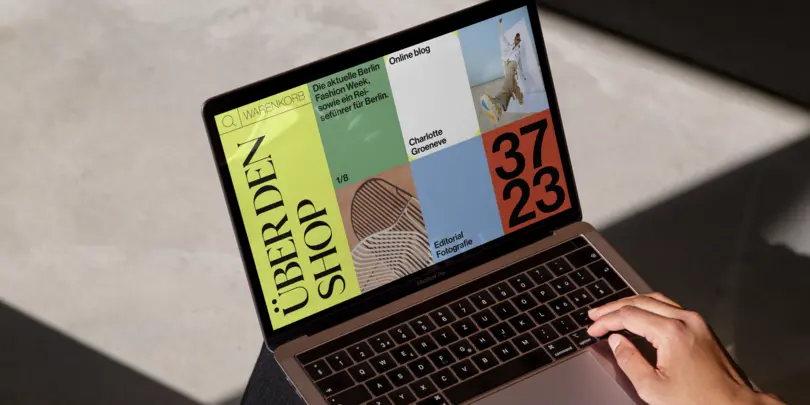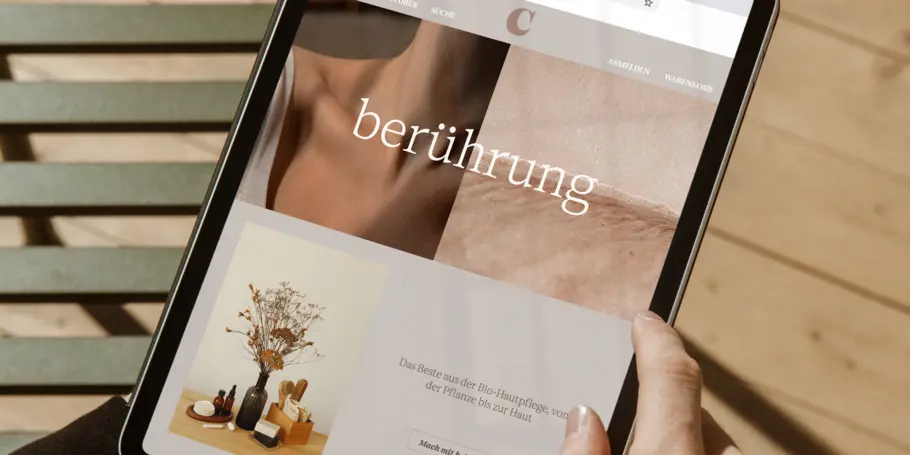
Wie ein verstärkter Fokus auf die digitale Transformation die Markenerwartungen der Kunden verändert hat.
„ Unabhängig von der Mission Ihrer Marke ist die Schrift entscheidend für den Aufbau und die Pflege Ihrer Kundenbeziehung. “
In den letzten zehn Jahren hat sich der digitale Wandel dramatisch auf die Kreation ausgewirkt. Wir haben erlebt, wie sich Marken vom Verkaufen zum Geschichtenerzählen bewegt haben. Und es sind die Kreativen, die diese Geschichten schreiben.
Vor nicht allzu langer Zeit fand das Marketing ausschließlich in Printmedien statt. Heute findet fast alles digital statt. 89 Prozent aller Unternehmen haben bereits eine „digital first“-Strategie eingeführt oder planen, dies zu tun. Und 91 Prozent der Unternehmen sind in irgendeiner Form an digitalen Initiativen beteiligt.
Wenn wir die Entwicklung des Marketings betrachten, war der entscheidende Treiber sicherlich die Verbreitung der mobilen Technologie. Doch die Corona-Pandemie war der Moment, an dem sich alles änderte. Das Abstandhalten und die Regelungen für den Aufenthalt zu Hause förderten die Nachfrage nach digitalen Schaufenstern und mobilen Websites. Dies öffnete die Tür für Innovation und Kreativität, führte aber auch zu einigen Hindernissen auf dem Weg zum neuen Normal.
In einer Welt nach der Pandemie sind die Erwartungen an das Branding so hoch wie nie zuvor.
Die Marke digital vermenschlichen
Während der Pandemie wurden den Kunden das Design, die Werte und die Moral von Marken bewusster als zuvor. Infolgedessen sehen sich Unternehmen mit der neuen Herausforderung konfrontiert, ihren Zweck digital darzustellen. Glücklicherweise können Designer dabei helfen. Neben der Möglichkeit, mit den neuesten digitalen Trends zu experimentieren, hat sich die Schrift zu einem wichtigen Faktor bei der Markenpositionierung entwickelt. Eine Schrift zu finden, die zu Ihren Markenwerten passt, hilft den Kunden, sich mit Ihrer Marke zu identifizieren und eine Verbindung mit ihr einzugehen.
Eine Offenes-Ohr-Mentalität entwickeln
Die Kunden erwarten heute mehr Kommunikation. Untersuchungen zufolge ist Hilfsbereitschaft eine der wichtigsten Erwartungen an Marken. Kunden setzen voraus, dass Marken auf sie eingehen und ein Forum für digitales Feedback bieten. Ob Helpdesk oder Hotline, die Kunden wollen einen Ansprechpartner und einen bilateralen Dialog mit den Marken, denen sie vertrauen. Um diesen Anforderungen zu genügen, müssen Marken jederzeit erreichbar sein und die Erwartungen ihrer Kunden erfüllen. Achten Sie bei der Auswahl der Designelemente für Ihr Branding darauf, dass Sie Schriften wählen, die technisch funktional und gut lesbar sein, damit Sie verlässlich mit Ihren Kunden kommunizieren können. Der Vorteil einer digitalen Präsenz besteht darin, dass Aktualisierungen schneller bei den Verbrauchern ankommen als im Rahmen der analogen Kommunikation.
Lokale und globale Reichweite
Mit der zunehmenden Digitalisierung von Marken ist die Zielgruppe für das Marketing heute internationaler denn je. Das bedeutet, dass digitale Vermarkter auf mehrere Kulturen und Sprachen eingehen müssen, damit sie ihren Markt erreichen. Um auf einer solch globalen Ebene zu kommunizieren, ist es wichtig, dass Sie Ihre Botschaft auf die erweiterten Märkte zuschneiden. Sie sollten Ihr Markenethos und Ihre Werte universell kommunizieren, indem Sie Fonts verwenden, die international funktionieren. Wenn Sie Ihr Leitbild auf Ihrer Website veröffentlichen, sollte das Design der Website darauf abgestimmt sein. Daher ist es wichtig, dass Ihre Fonts viele Sprachen und Schreibsysteme unterstützen und auf globaler Ebene Anklang finden. Ob Sie es glauben oder nicht: 95 Prozent des Webdesigns besteht aus Typografie. Und Studien zeigen, dass Marken weniger als 50 Millisekunden Zeit haben, um einen guten ersten Eindruck zu hinterlassen.
Kontinuierliche Verbesserungen
Eine weitere Herausforderung besteht darin, die sich ständig ändernden Erwartungen der Verbraucher zu erfüllen. In der digitalen Welt ändern sich die Dinge permanent, da stetig neue Technologien entwickelt werden und weil von Marken erwartet wird, dass sie mit den neuesten Trends Schritt halten. Um sich anzupassen, müssen Unternehmen möglicherweise einen Social-Media-Berater einstellen oder neue Technologien erlernen, um mit den Wettbewerbern auf dem Markt mitzuhalten. So haben viele Marken inzwischen eine mobile Website, die ihre Desktop-Site ergänzt. Da 85 Prozent der Erwachsenen der Meinung sind, dass die mobile Website eines Unternehmens genauso gut oder besser sein sollte als die Desktop-Website, haben viele Anbieter sogar eine mobile App eingeführt. Wenn neue Updates des Betriebssystems veröffentlicht werden, muss die App getestet werden, um ihre Funktionalität zu gewährleisten. Wenn Sie mit diesen kontinuierlichen Verbesserungen Schritt halten, wird Ihr Unternehmen auf dem Markt wettbewerbsfähig bleiben.
Loyalität aufbauen
In der digitalen Welt spielt die Schaffung von Vertrauen beim Aufbau eines Kundenstamms eine große Rolle. Laut der aktuellen „Edelman Trust Barometer“-Umfrage kaufen oder befürworten 58 Prozent der Menschen Marken auf der Grundlage ihrer Überzeugungen und Werte. Marken müssen bei ihrer Zielgruppe ein Gefühl der Zugehörigkeit und des Vertrauens aufbauen, um langfristige Kundenerfahrungen zu schaffen. Die Qualität der Designelemente trägt dazu bei, eine einheitliche Stimme zu schaffen, die diese Gefühle unterstützt.
Die Wahl einer Schrift, die über alle Plattformen hinweg konsistent ist, sorgt dafür, eine stabile Vertrauensebene zu schaffen: Die Kunden erkennen Sie wieder und assoziieren Ihre Marke mit der Schrift. Wenn Kunden die Typografie von Verizon sehen, erkennen sie die Marke sofort, egal ob sie die App oder die Website ansehen, weil sie über alle Kanäle hinweg einheitlich erscheint.
Unvergesslich werden
Experten gehen davon aus, dass wir pro Tag mit 10.000 bis 13.000 Werbebotschaften konfrontiert werden. Daher ist es wichtig, dass Ihre Website, Ihre App und Ihre Social-Media-Kanäle ein einzigartiges Element aufweisen, das den Kunden hilft, sich an Sie zu erinnern. Die Outdoor-Modemarke Patagonia widmet einen großen Bereich auf seiner Website dem Erzählen seiner Geschichten. Die Marke setzt auf einprägsames Storytelling, das ihre Kernmission und Werte unterstreicht. Wenn Sie sich die Geschichten ansehen, werden Sie feststellen, dass auch die Schrift ganz genau auf die Marke abgestimmt ist, um ihr eine persönliche Note zu verleihen. Es ist wichtig, dass Ihr Branding positive Erfahrungen schafft, damit sich Ihre Kunden an die schönen Momente erinnern, die sie mit Ihrer Marke erleben.
Die Schrift spielt eine entscheidende Rolle für ein gutes Benutzererlebnis. Sobald Sie Ihre zentralen Markenwerte und Ihre Mission definiert haben, können Sie die Schrift nutzen, um eine langfristige Kundenbeziehung aufzubauen. Dazu gehören die Wahl einer Schrift, die zu Ihrer Markenstimmung passt, sowie die Verwendung von Bildern, die bei den Verbrauchern Emotionen auslösen. Unabhängig vom Kern Ihrer Marke ist die Schrift entscheidend für den Aufbau und die Pflege Ihrer Kundenbeziehung.